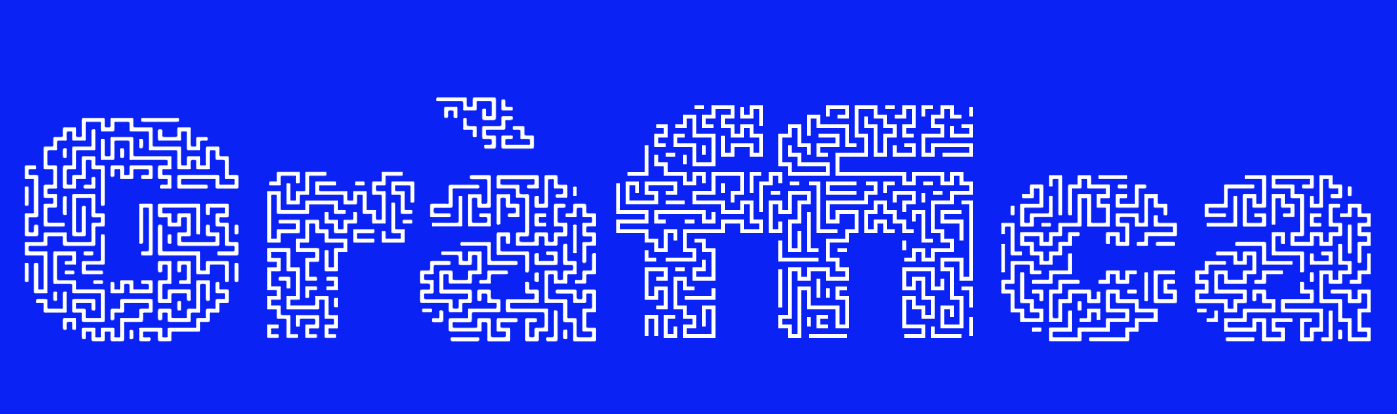
Generative Fonts presenta 28 fuentes generadas por un algoritmo
El estudio NaN ha creado una serie de filtros para Glyphs con los que modificar una fuente aplicándole diferentes estilos gráficos a cada cual más irreverente.
NaN es un estudio berlinés que nació este mismo 2020 con el propósito de diseñar tipografías decorativa y experimentar con los procesos creativos. Uno de sus primeros proyectos es Generative Fonts, una colección de fuentes decorativas generadas proceduralmente. Más o menos. Te cuento.
En general, mediante unas variables —aleatorias o no— podemos alimentar un algoritmo y que este nos devuelva diferentes resultados. Un ejemplo: si a un algoritmo de suma aritmética le introducimos un 2 y un 3, nos devolverá un 5; y si le damos números diferentes, nos dará un resultado diferente pero siempre lógico dentro de las reglas marcadas. Esto puede escalarse tanto como se quiera para generar música, arte o incluso planetas con su propia fauna y flora.
Bien. ¿Se puede hacer lo mismo en tipografía? Sí y, de hecho, desde los años 90 se viene experimentando con ello. El ejemplo más popular es, probablemente, FF Beowolf (1990) de Erik van Blokland y Just van Rossum que «presenta una función de aletoriedad en su código que hace que sus formas cambien cada vez que se imprimen, por lo que ninguna letra se verá igual dos veces.»
Mientras que Beowolf actuaba a nivel Postscript al imprimir, en este caso hablamos de una intervención al generar las propias fuentes. El algoritmo viene en forma de filtros para Glyphs donde la variable es la fuente —o los iconos o cualquier otro vector— que queramos modificar. Hacemos click y a esperar a que el algoritmo nos devuelva el resultado.
Los filtros (algoritmos) disponibles son prosaicamente generativos (Maze, Storm), texturizados (Distresed, Dirt), ilustrativos (Bubbles, Beastly), hechos a mano (Doodle Triangles, Scribble), o simplemente únicos (Glitch Pop, Sea Camouflage). Para ponerlo incluso más fácil, Generative Fonts nos presenta ya el resultado con 28 fuentes generadas a partir de Rubik. Como el proyecto ha sido liberado (subvencionado) por Google Fonts todas las fuentes están disponibles con licencia libre SIL v1.1; los filtros también son de código abierto.
Teóricamente, sí nos encontramos ante tipografía generada por un algoritmo. En la práctica, sin embargo, es la misma fuente pasada por diferentes filtros. ¿Hace esto que sea menos interesante el resultado? En absoluto, aunque sí pienso que le resta espectacularidad a lo que en un principio parecía prometer.